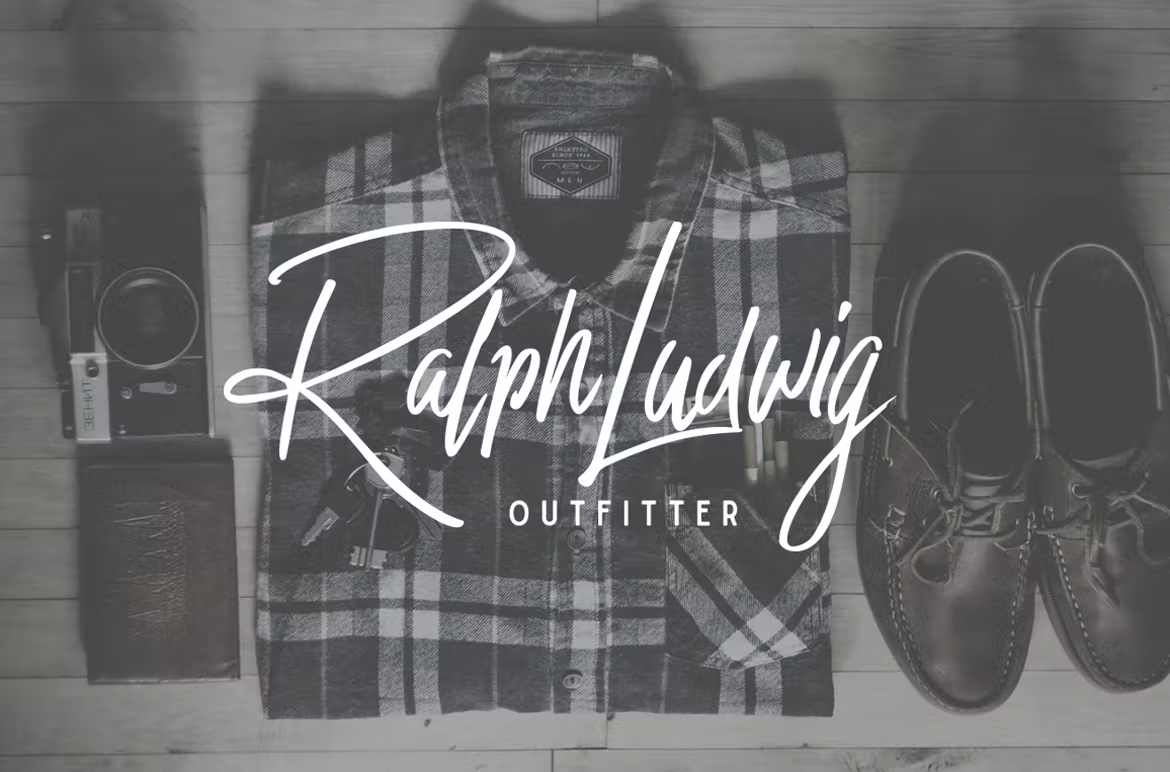
Bird House Script Font
Description de Bird House Script Font
Bird House Script est une police manuscrite conçue à l’aide de marqueurs. Cette police est parfaite pour la marque, la signature et bien plus encore. Il comprend les caractères standard majuscules, la ponctuation et la prise en charge de plusieurs langues.